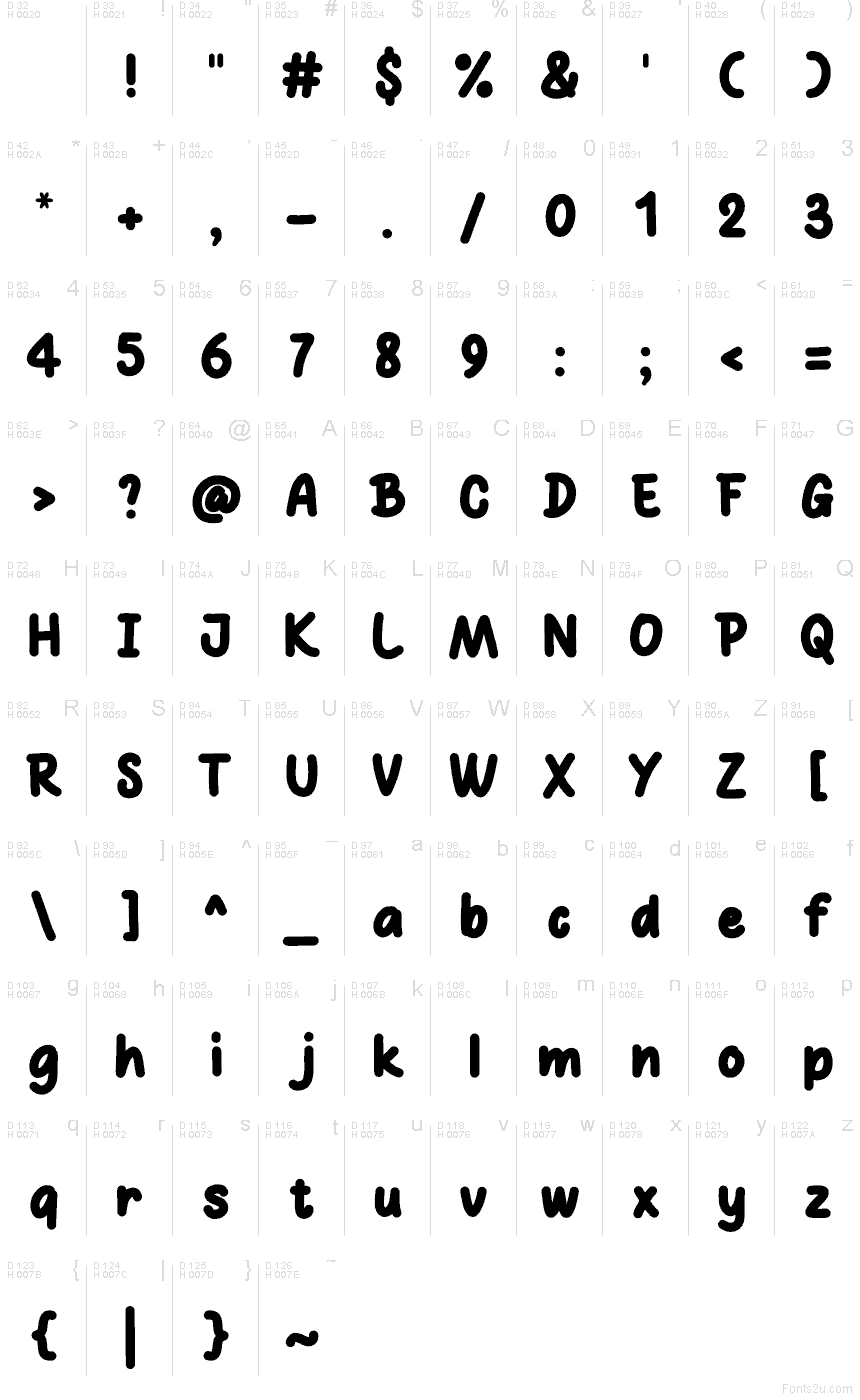
Coffee Free
Coffee від Hello Good Studio — це безкоштовний рукописний шрифт з м'якими, заокругленими літерами та розслабленим, ритмічним накресленням. Плавний потік ліній, м'які вигини та прості поєднання надають йому повсякденного й затишного «кавового» характеру.
Coffee чудово підійде для меню кафе, пакування напоїв, логотипів пекарень, графіки для соцмереж та запрошень: його форма виглядає індивідуально та душевно, проте залишається охайною. Шрифт також чудово працює на вивісках, етикетках та в коротких цитатах, де потрібен дружній рукописний акцент.